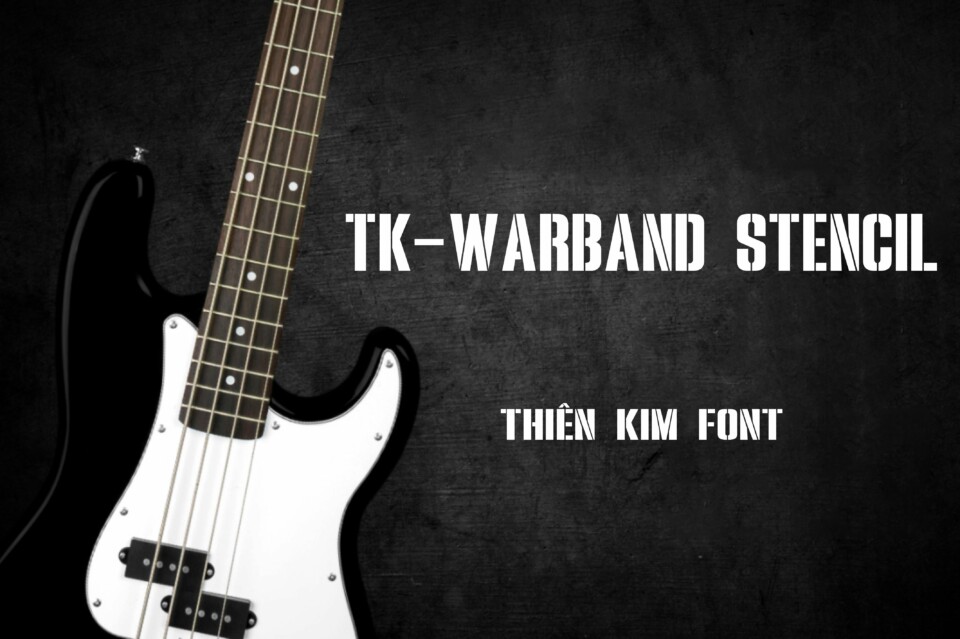
Font việt hoá TK-Warband Stencil
Giới thiệu về Font việt hoá TK-Warband Stencil
Trong thế giới đồ họa, việc lựa chọn một Font Miễn Phí phù hợp là yếu tố then chốt để tạo nên hồn cho tác phẩm. Font việt hoá TK-Warband Stencil là một bộ phông chữ mang đậm phong cách stencil (khuôn chữ đục lỗ) đầy mạnh mẽ và cá tính. Được thiết kế dựa trên cảm hứng từ các ký hiệu quân sự và bảng hiệu công nghiệp, bộ phông này mang lại cảm giác vững chãi, nghiêm túc nhưng không kém phần hiện đại. Phiên bản việt hoá giúp người dùng tại Việt Nam dễ dàng sử dụng trong các phần mềm thiết kế mà không lo lỗi font hay thiếu dấu tiếng Việt đặc trưng.
Đặc điểm nổi bật của Font việt hoá TK-Warband Stencil
Phong cách thiết kế độc đáo
Đặc trưng của Font việt hoá TK-Warband Stencil nằm ở các nét cắt dứt khoát và khoảng hở tinh tế giữa các nét chữ. Điều này tạo nên hiệu ứng thị giác giống như chữ được phun sơn qua khuôn đồng, rất phổ biến trên các thùng hàng hoặc phương tiện vận tải quân sự. Kiểu dáng này cực kỳ phù hợp cho các dự án liên quan đến trò chơi điện tử, áp phích phim hành động hoặc các nhãn hiệu thời trang đường phố bụi bặm.
Khả năng ứng dụng đa dạng
Dù mang hơi hướng cứng cáp, nhưng bộ phông chữ này vẫn đảm bảo tính dễ đọc cao. Bạn có thể sử dụng nó cho các tiêu đề lớn, logo thương hiệu hoặc dùng trang trí trong các bài giảng về lịch sử, quân sự tại trường học. Khả năng tương thích tốt với các hệ điều hành giúp quá trình cài đặt diễn ra nhanh chóng và thuận tiện cho cả giáo viên và học sinh.